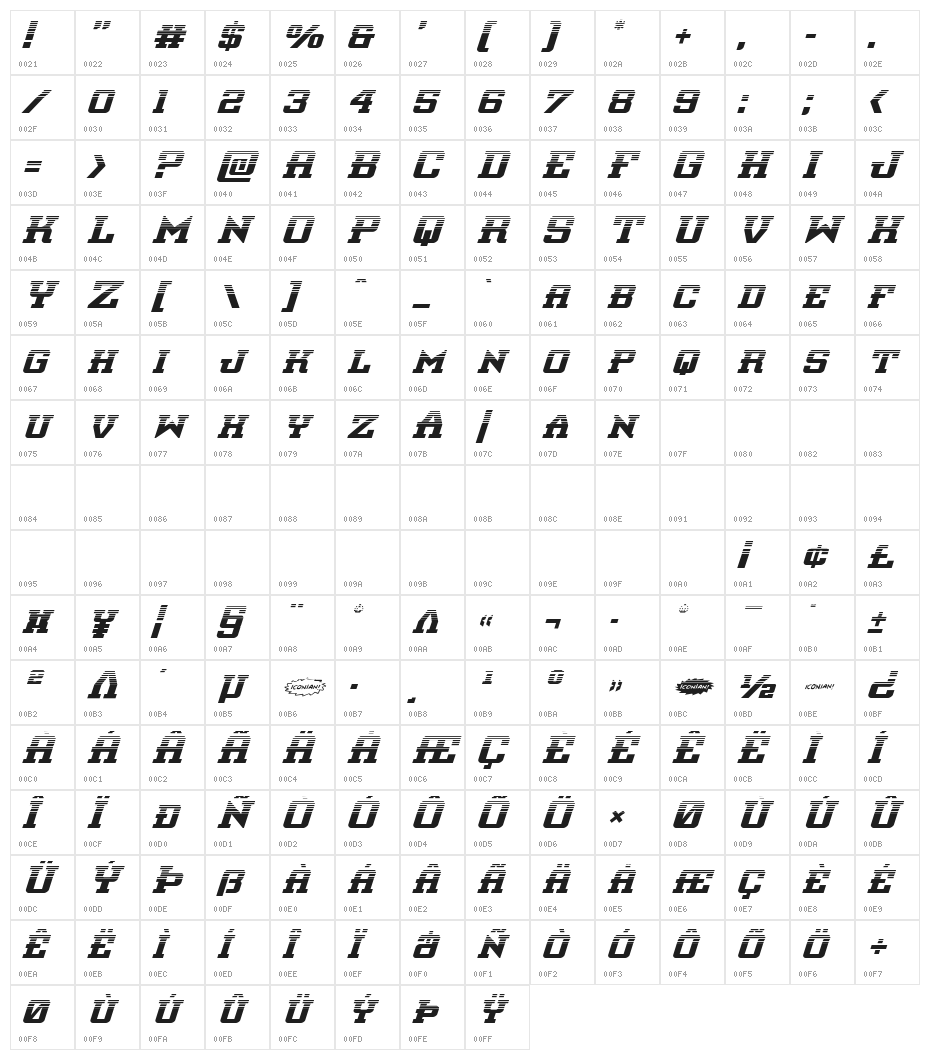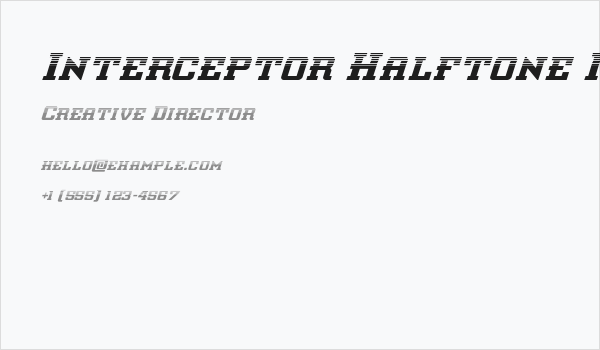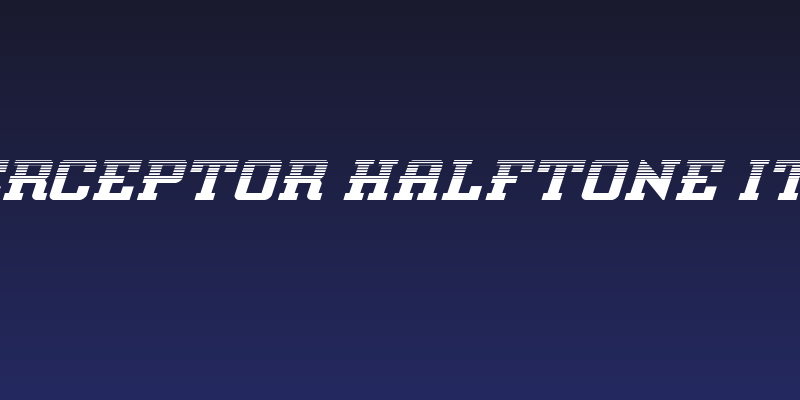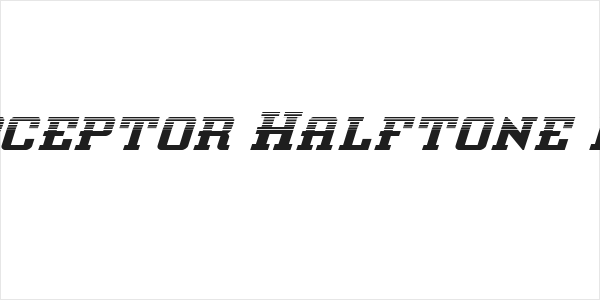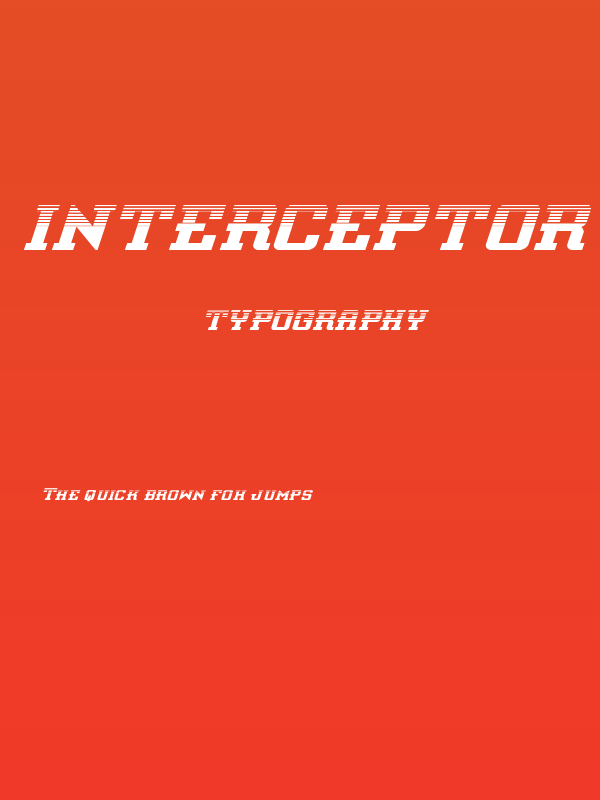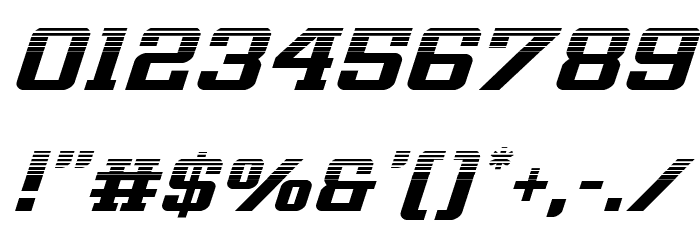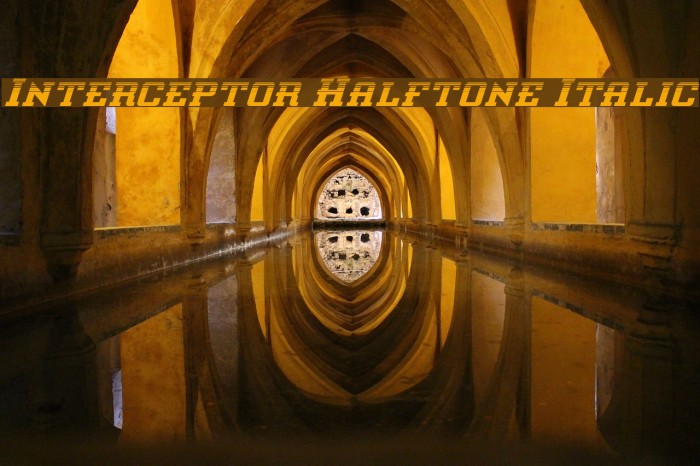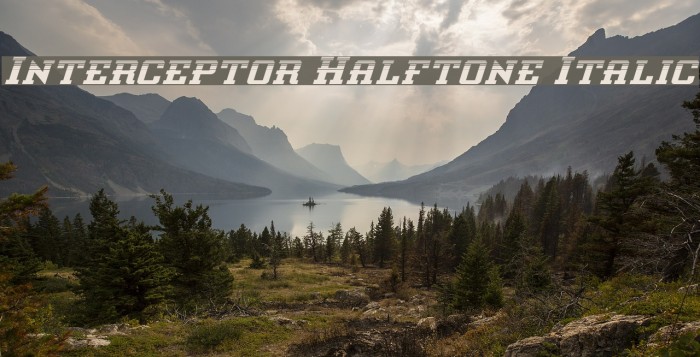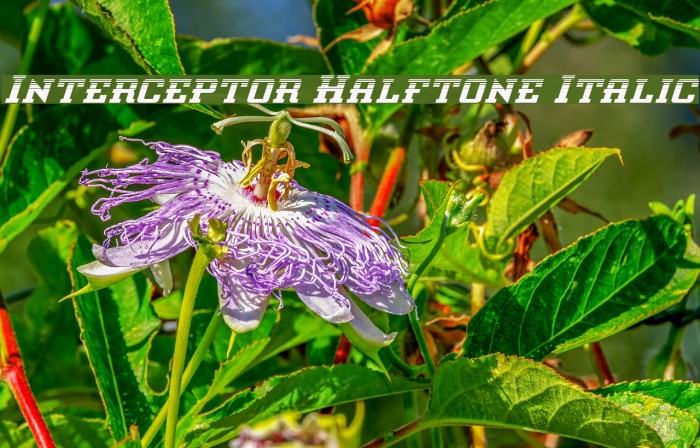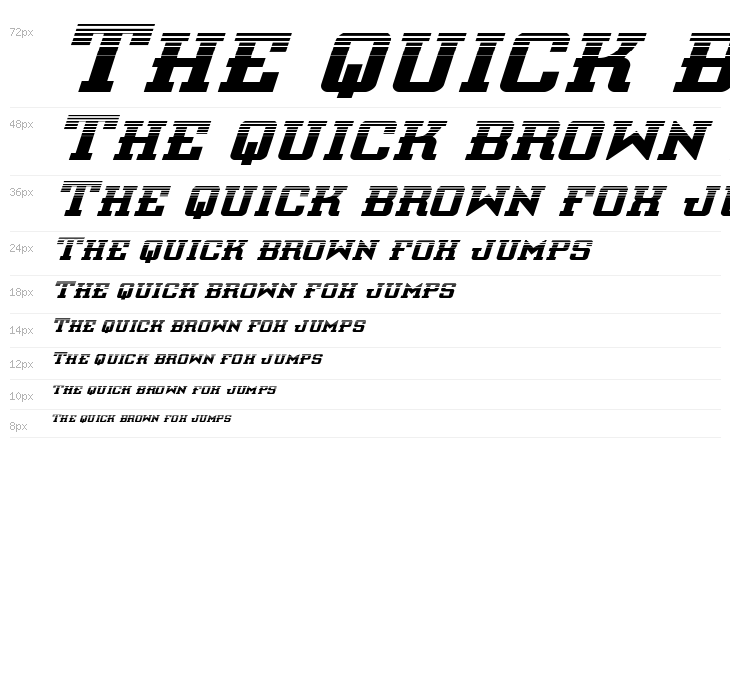
Interceptor Halftone Italic Font
| Proyectos propuestos | Ideal for sports branding, automotive designs, posters, and any project needing a modern, energetic touch. |